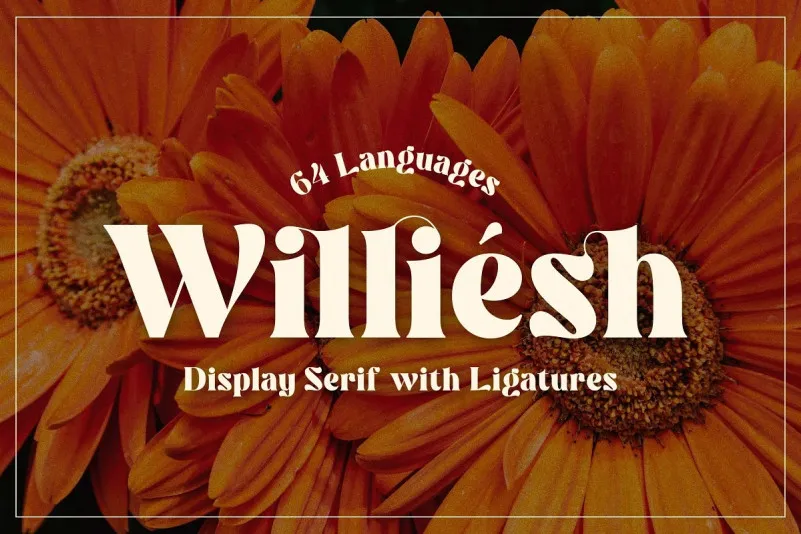
Williesh Font
A Willish Font é uma elegante tipografia que combina elementos modernos com um ar retro, oferecendo um visual claramente definido e descontraído ao mesmo tempo. Inspirada no famoso logotipo minimalista, essa fonte perfeita para projetar templates, brochuras, vídeos, marcações publicitárias e logomarcas, entre outras aplicações. Ela é especialmente adequada para dar um toque único a logos de marca, monogramas ou citações pull. Kavaloora tem 18 ligaturas únicas e gêlos alternativos, além de números e pontuação, tornando-a uma escolha perfeita para designers em busca de algo diferente e fascinante no seu trabalho.